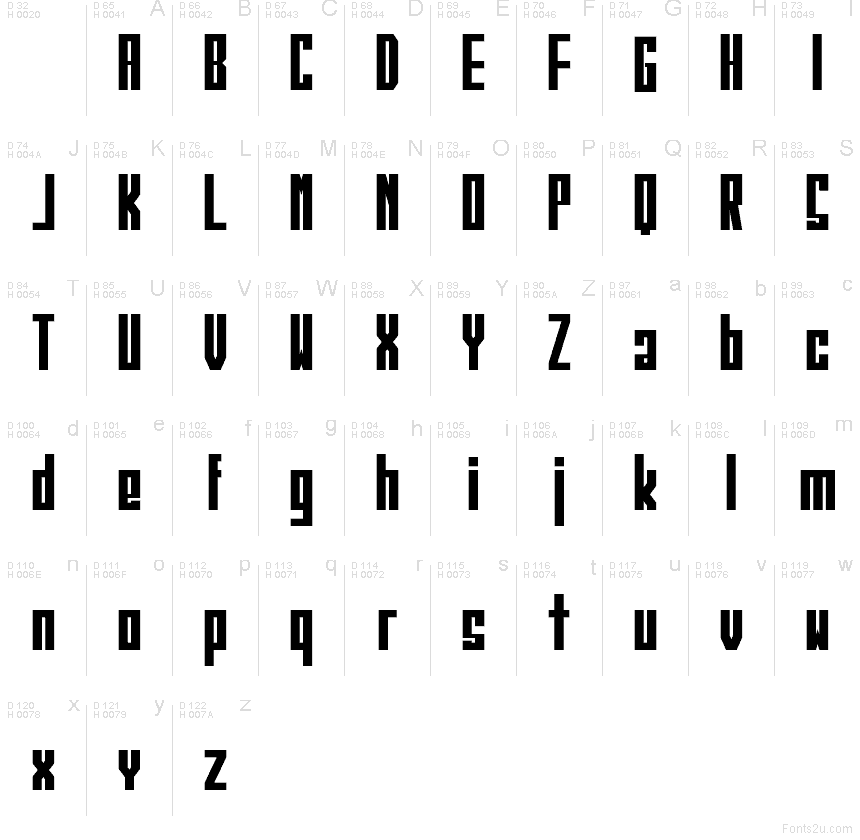
Vanishing Condensed od Vladimira Nikolice je bezplatné techno display písmo, které definují vysoké obdélníkové tahy, hranaté zlomy a hluboké výřezy, díky nimž písmena působí téměř jako bludiště. Tento opakující se vzor pevných černých sloupců, přerušovaný ostrými vertikálními kanály, dodává designu napjatý, mechanický rytmus namísto hladkého geometrického toku.
Skvěle funguje u názvů her, sci-fi plakátů, klubových letáků, úvodních obrazovek aplikací a streamovacích miniatur, kde hraje hlavní roli kompaktní silueta s vysokým kontrastem. Nejlépe vynikne u krátkých nadpisů a log, protože úzká struktura a ostré rohy vytvářejí hustou grafickou texturu, díky které slova působí promyšleně a energicky.